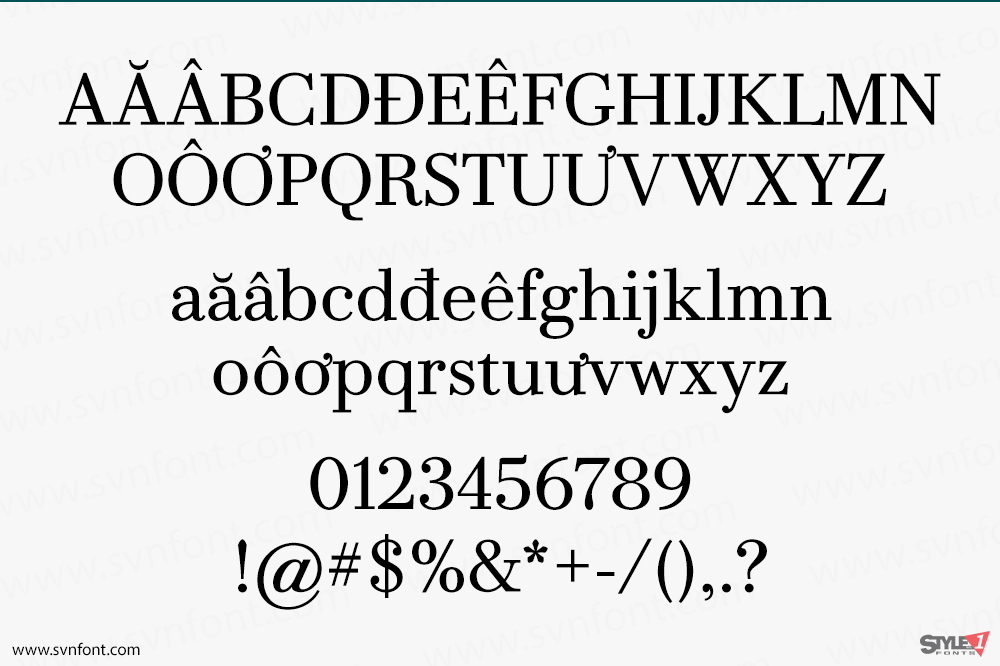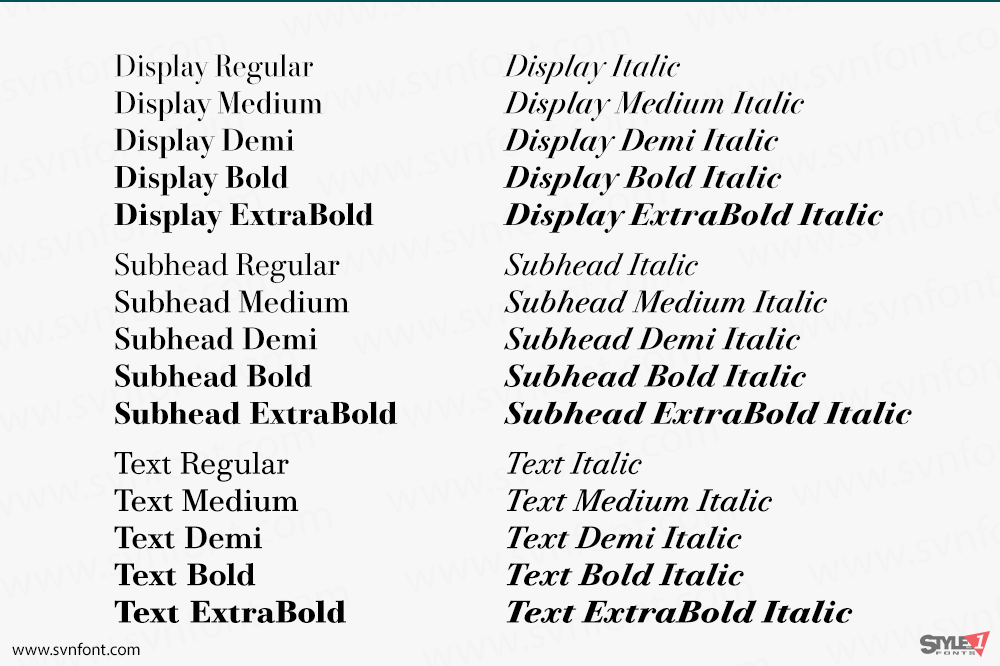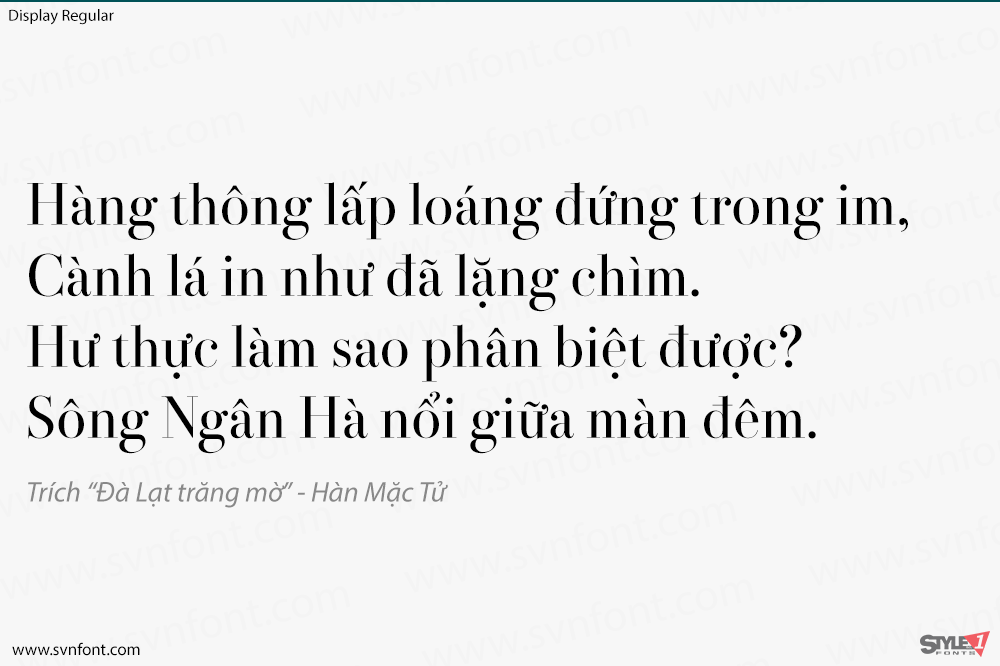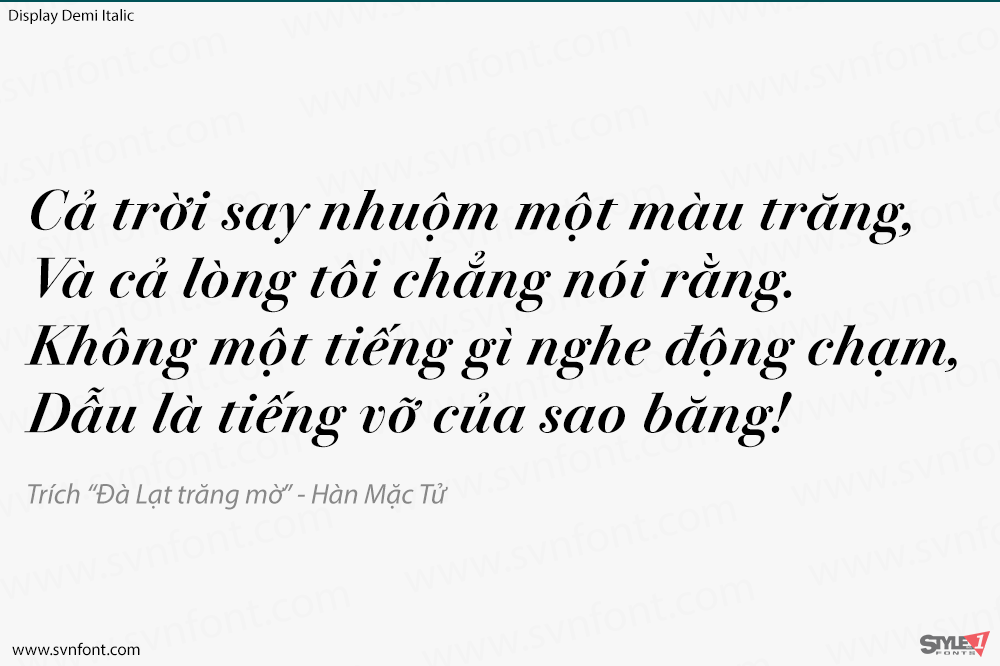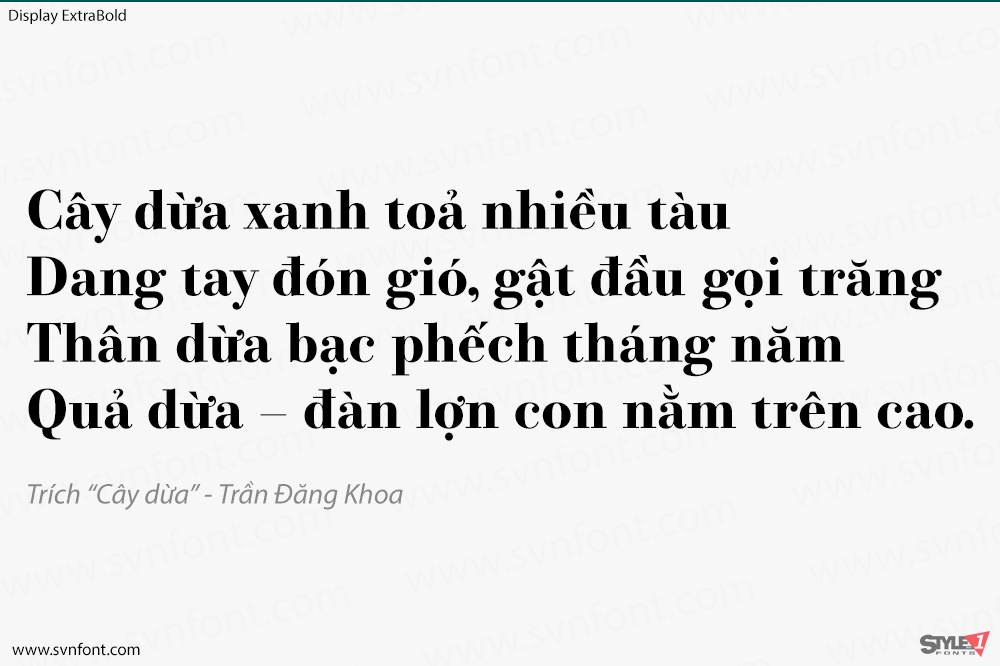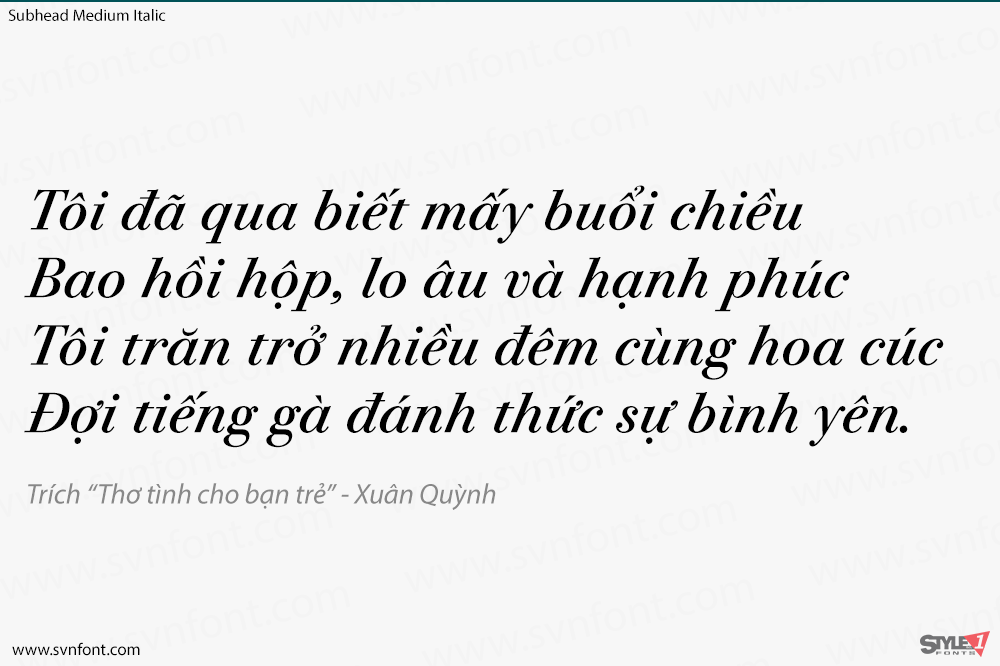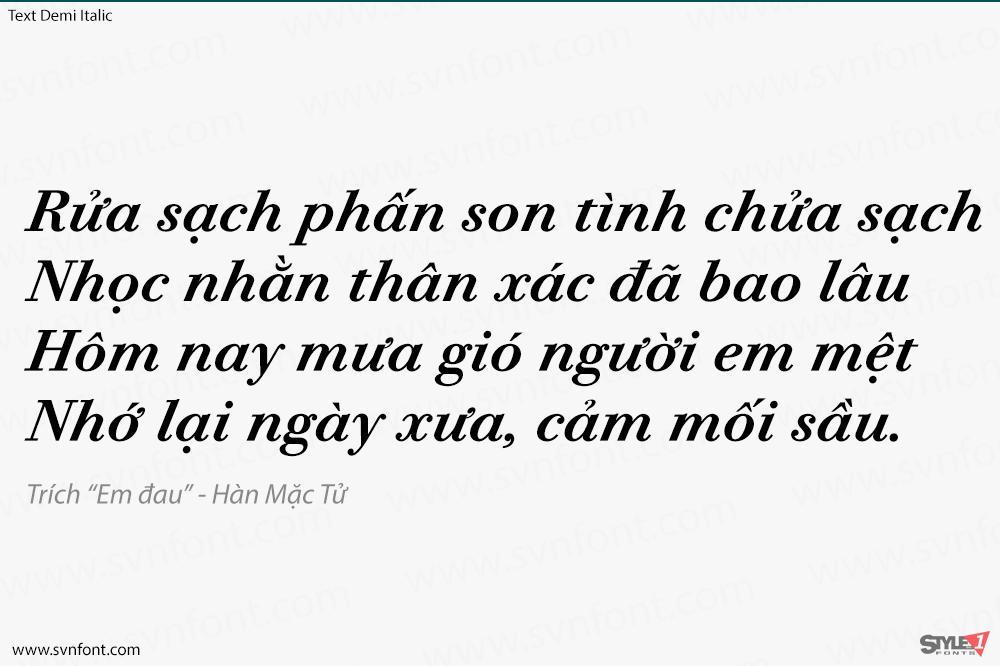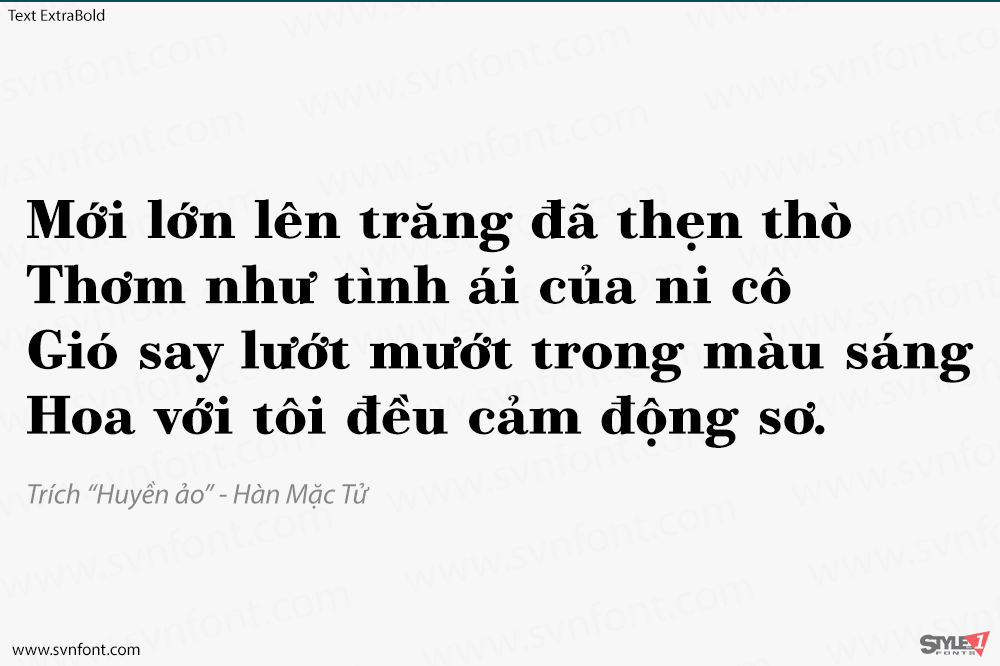
Bodoni PT, một kiểu chữ serif đương đại mang đậm dấu ấn lịch sử, là một hệ thống kiểu chữ linh hoạt với các phông chữ dành cho cả đoạn văn dài và tiêu đề kích thước cực lớn. Bodoni PT dựa trên tỷ lệ và các đặc điểm nổi bật của các kiểu chữ của Giambattista Bodoni, “vua của các nhà in và nhà in của các vị vua.” Đồng thời, Bodoni PT hoàn toàn thích nghi với các điều kiện hiện đại. Nó hoạt động tốt trên màn hình và khi in, trông tự nhiên trong văn bản và thiết kế của nó không có vẻ lỗi thời.
Bodoni PT có độ đậm từ Regular đến Extrabold và sự phân cấp kích thước quang học được thực hiện đầy đủ: Text styles (kiểu văn bản) dành cho kích thước nhỏ; Subhead styles (kiểu phụ đề) hoạt động tốt nhất cho kích thước trung bình; Display styles (kiểu hiển thị) dành cho kích thước lớn và cực lớn. Tổng cộng, có 15 kiểu đứng thẳng và 15 kiểu in nghiêng tương ứng, hai phông chữ biến đổi (variable fonts) cũng như một kiểu trang trí đặc biệt.
Kiểu chữ này có bộ ký tự mở rộng. Tất cả các kiểu đều hỗ trợ các ngôn ngữ châu Âu dựa trên bảng chữ cái Latin và Cyrillic. Tất cả các kiểu đều có đầy đủ các khả năng typographic: Chữ hoa nhỏ (small caps), Số tỷ lệ và số dạng bảng (proportional and tabular numbers), Số kiểu cũ và số chữ hoa nhỏ (old style and small-cap figures), Chỉ số (indices), Mũi tên (arrows).
Nhà thiết kế chính của Bodoni PT là Dmitry Kirsanov, một chuyên gia lớn về các kiểu chữ của Giambattista Bodoni. Bên cạnh ông, các nhóm thiết kế và công nghệ của Paratype cũng đã tham gia vào việc phát triển kiểu chữ này. Bodoni PT được phát hành vào năm 2021.
Nhà thiết kế: Dmitry Kirsanov, Alexander Lubovenko, Dmitry Goloub, Nick Nedashkovsky
Nhà phát hành: Paratype